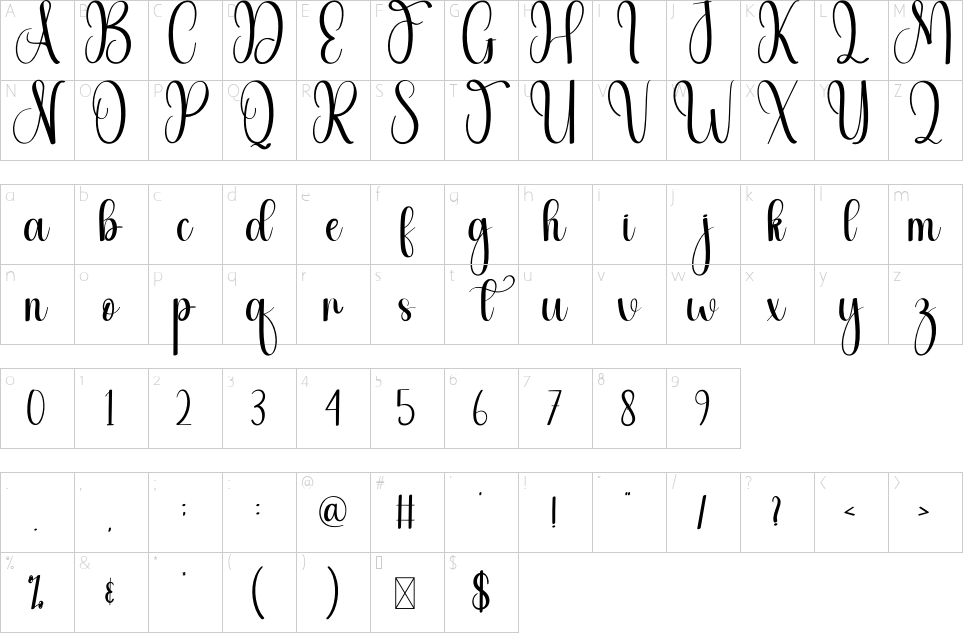
A fonte ‘Argument’ oferece um design moderno e elegante, perfeitamente adequada para uso em materiais de design gráfico. Desenvolvida pelo designer William Jhordy, essa fonte tem uma arquitetura sofisticada que se assemelha a uma conversa entre linhas e caracteres, criando um efeito visual interessante. Se você busca uma fonte fresca e moderna para seus projetos, Argument pode ser uma escolha excelente. Ela já foi baixada 445 vezes, o que indica sua popularidade entre designers e criativos. Com ‘Argument’, você pode adicionar um toque de sofisticação e originalidade a suas composições de texto. Download esta fonte gratuitamente e experimente o poder de Argument para personalizar suas criações.